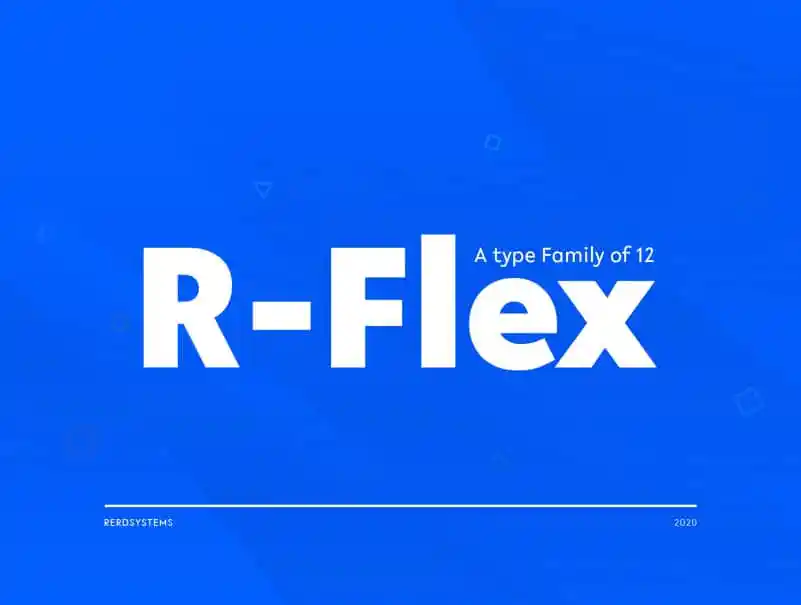
R-Flex Sans Serif Font – Download Grátis
R-Flex Sans Serif é uma elegante família de fontes sans serif que traz à tona a modernidade do tipo geométrico com um toque de grotesco. Este design exclusivo, criado pelo designer vikers, oferece uma variedade extensa de pesos e opções, incluindo 12 pesos variados para atender às necessidades mais específicas do projeto. Além disso, você encontrará 6 linhas rectas e suas respectivas itálicas, tudo isso com suporte linguístico completo que inclui fracionamento, números tabulares, ligaduras, além de muitos outros recursos únicos. A R-Flex Sans Serif foi projetada para atender a um leque amplo de usos, incluindo design gráfico, publicidade e editoriais. Suas características poderosas e flexíveis no formato aberto tornam a fonte perfeitamente adaptável para ambientes digitais, como web e aplicações móveis, bem como para uso em sinalização e mídias corporativas. Este é um tipo de fonte que se destaca por sua capacidade única em comunicar claramente e estilisticamente, tornando-se uma ótima escolha para qualquer projeto visual. Com R-Flex Sans Serif na sua carteira de recursos, você pode explorar o máximo da potência do design gráfico contemporâneo.